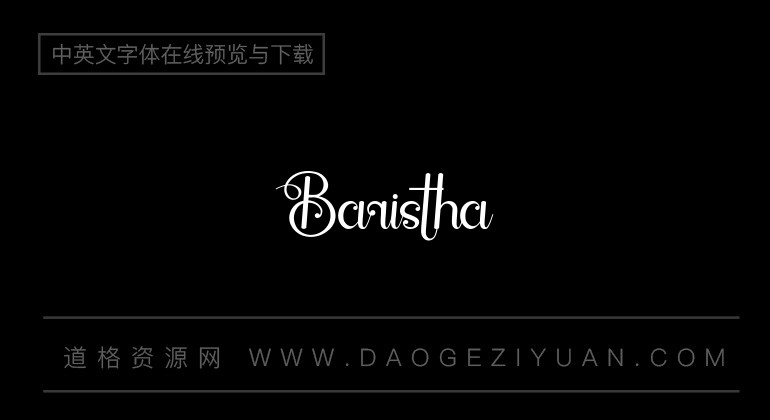
Baristha 是一种优美且流畅的手写风格字体。它被设计成适用于多种场合,例如品牌标志、包装设计、海报、手册和书籍等。该字体具有干净、简单和现代的感觉,同时又不失温暖和亲切感。Baristha 字体包含了大写字母、小写字母、数字、标点符号和其他特殊字符,使得它非常适合于各种设计需求。此外,该字体还有多种字重可供选择,以适应不同的设计需求。内容介绍
Baristha是一款非常不错的手写艺术字体,具有很好的视觉感,适合于文化类的宣传设计、商业类品牌的广告和产品包装设计以及个性化文字排版等较多场景。